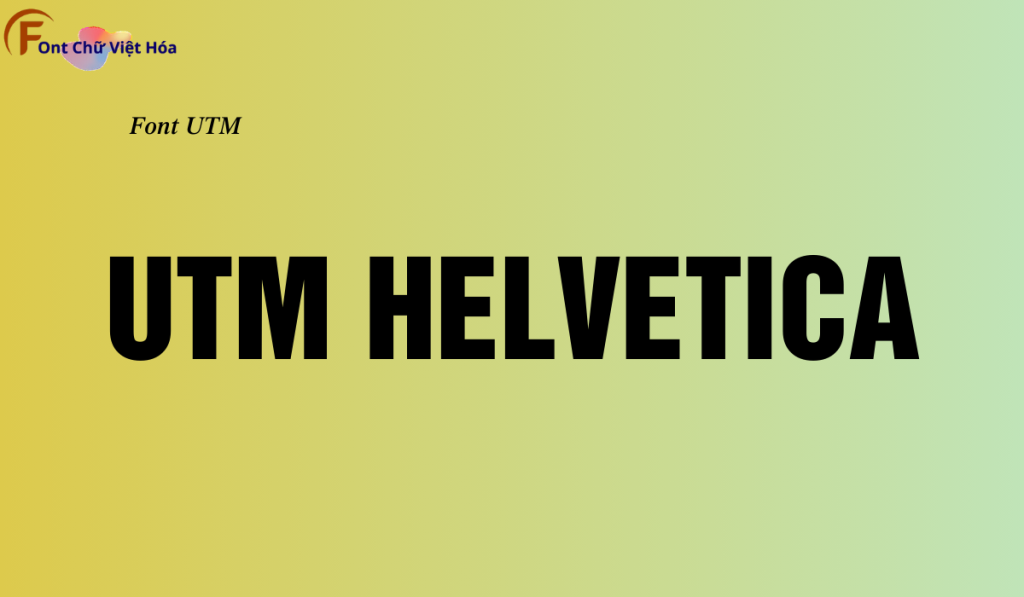
Font UTM Helvetica Việt Hóa
Tác giả: UTM Helvetica
Bộ Font: UTM
Phân loại: Hiện đại, Chuyên nghiệp
Kiểu chữ: Sans-serif
Độ dày: Regular, Bold, Italic, Bold Italic
Font UTM Helvetica Việt Hóa là một font chữ không chân hiện đại, thuộc bộ font UTM. Được thiết kế với mục tiêu mang lại sự đơn giản và hiệu quả, font này lý tưởng cho các dự án thiết kế như giao diện người dùng, ứng dụng di động, và website. Với các nét chữ rõ ràng và độ dày đều đặn, Font UTM Helvetica Việt Hóa không chỉ dễ đọc mà còn tạo cảm giác hiện đại và chuyên nghiệp. Việc Việt hóa font giúp người dùng dễ dàng tích hợp vào các thiết kế tiếng Việt, mang lại sự tiện lợi và nâng cao tính thẩm mỹ.